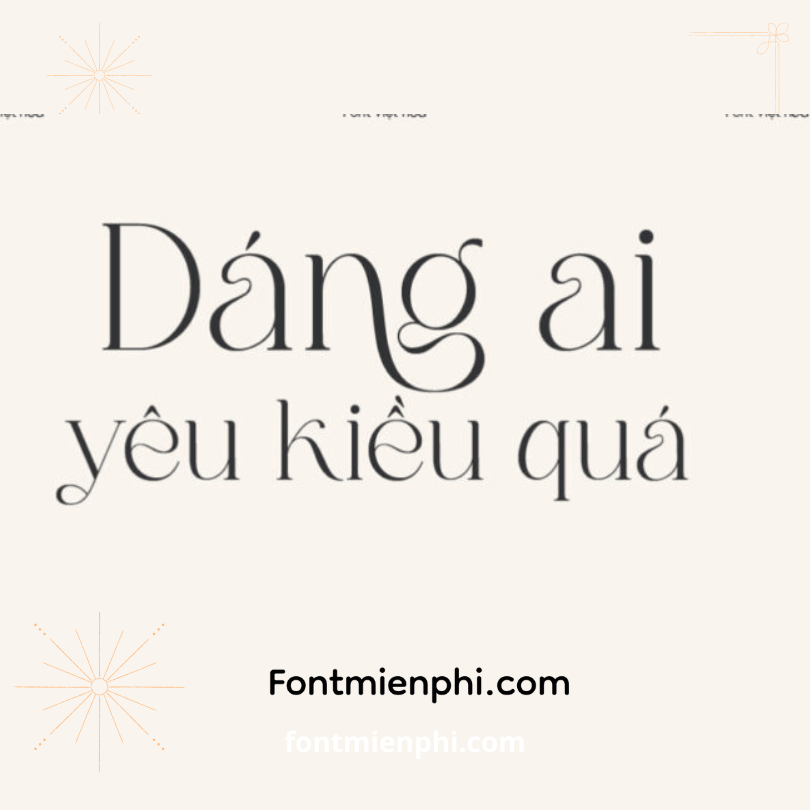
Font Việt hóa 1FTV VIP Stylish Mother – Giải Pháp Typography Chuyên Nghiệp Cho Thiết Kế Đỉnh Cao
Font Việt Hóa 1FTV VIP Stylish Mother là bộ font chữ cao cấp, được thiết kế tỉ mỉ với phong cách sang trọng, phù hợp cho các dự án đòi hỏi tính thẩm mỹ và chuyên nghiệp. Với khả năng tương thích hoàn hảo với tiếng Việt, font chữ này trở thành lựa chọn hàng đầu cho designer, marketer, và các nhà sáng tạo nội dung.
✔ Hỗ Trợ Tiếng Việt Chuẩn: Đầy đủ dấu và ký tự đặc biệt, đảm bảo hiển thị rõ ràng, mượt mà trên mọi nền tảng.
✔ Phong Cách Độc Đáo: Nét chữ thanh lịch, kết hợp giữa hiện đại và cổ điển, phù hợp với đa dạng ngữ cảnh (logo, banner, typography nghệ thuật).
✔ Đa Dạng Ứng Dụng: Dùng cho in ấn, thiết kế đồ họa, quảng cáo, website, và các dự án sáng tạo khác.
- Chất Lượng VIP: Nét chữ sắc nét, không lỗi font khi in ấn hoặc hiển thị kỹ thuật số.
- Tính Linh Hoạt: Phù hợp với nhiều phong cách thiết kế từ tối giản đến cầu kỳ.